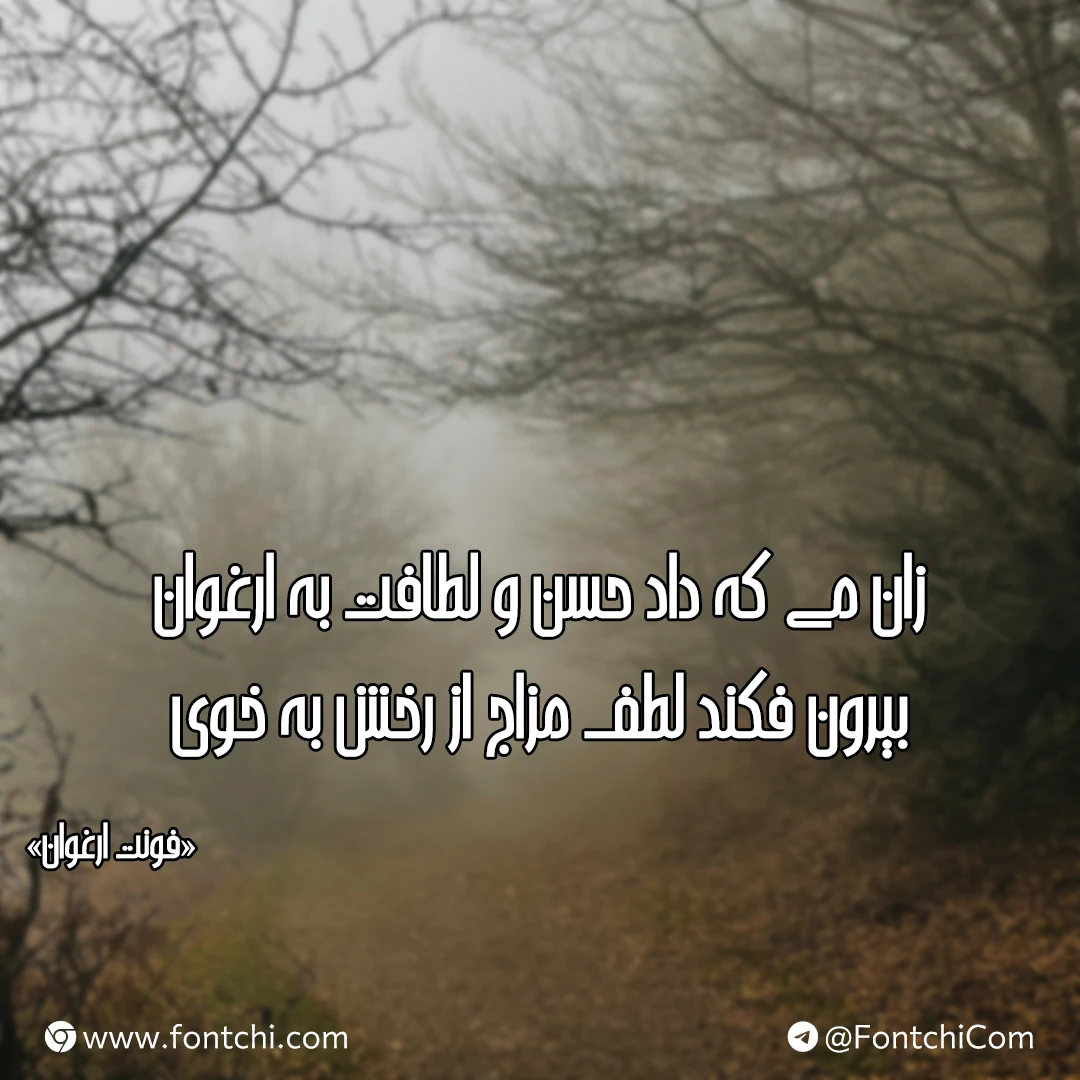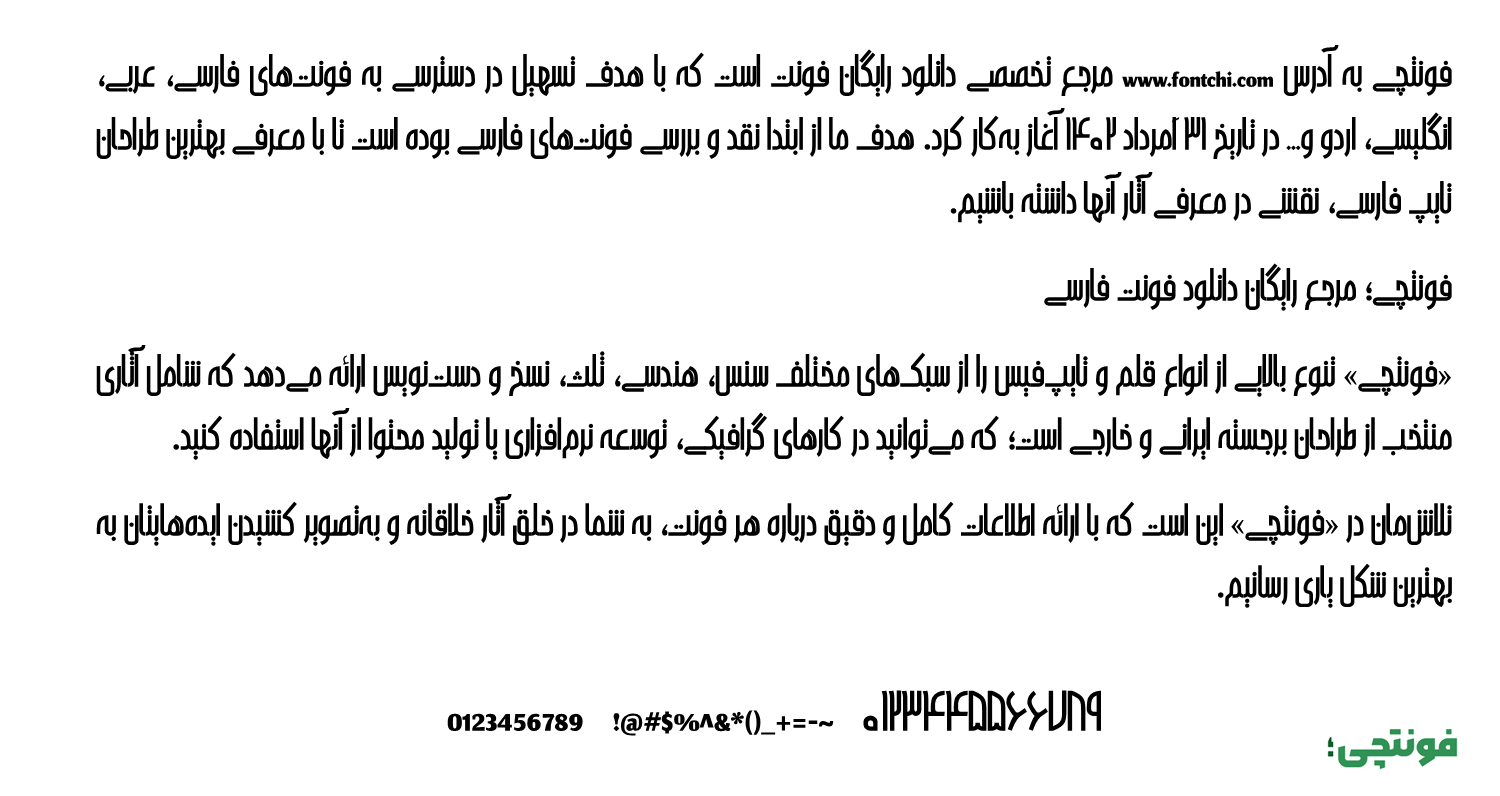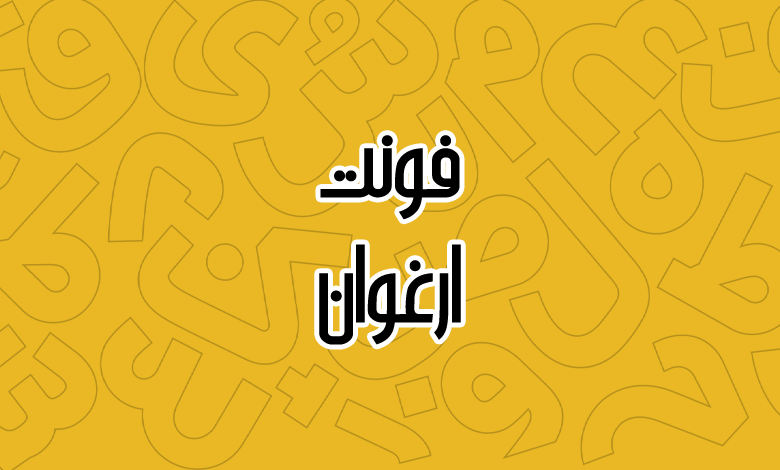
فونت ارغوان (A Arghavan)
فونت ارغوان (به انگلیسی: Arghavan) از سری فونت‌های نمایشی با وزن ضخیم بولد (Bold) است که می‌توانید از آن برای عناوین و متون کوتاه استفاده کنید. فونت فارسی ارغوان دارای ظاهری با ارتفاع بالا و کشیده است که برای جلب توجه در متون تبلیغاتی یا عناوین می‌تواند مورد استفاده قرار گیرد.
طراح این فونت محمو عموئی است که از سبک خاصی برای نقطه‌گذاری این فونت استفاده کرده است. در برخی حروف نقطه‌های دوتایی و سه‌تایی این فونت در کنار یکدیگر و در برخی ترکیبات به منظور نمایشی کردن، به صورت عمود جای گرفته‌اند.
فونت ارغوان از زبان فارسی پشتیبانی کاملی دارد. علاوه بر این از زبان عربی نیز با همین سبک پشتیبانی می‌کند. تنها کاستی برای این زبان، ناهماهنگی اعراب در برخی ترکیبات خاص است. همچنین برای بخش اعداد، به‌جای استفاده از اعداد استاندارد «۰۴۵۶» عربی، از اعداد فارسی «۰۴۵۶» استفاده شده است.
زبان انگلیسی نیز توسط این فونت پشتیبانی می‌شود. اما به دلیل اینکه گلیف اختصاصی خود را نداشته و از قلم دیگری وام گرفته شده است، اندازه حروف کوچکتر از نسخه فارسی بوده و همچنین سبک متفاوت‌تری را دارد. شاید بهتر باشد از فونت مشابه برای زبان انگلیسی استفاده کنید.
هدف از طراحی فونت فارسی ارغوان، نمایشی بوده است. از این فونت می‌توانید برای متون کوتاه چند کلمه‌ای استفاده کنید که جنبه شعار یا جلب توجه داشته باشند. برخی از کاربردهای این قلم عبارتند از:
• استفاده در عناوین کتاب و مجلات
• استفاده بر روی بسته‌بندی محصولات
• استفاده برای تبلیغ محصولات در متن شعارهای برند
• استفاده بر روی تامنیل ویدئوها یا تصاویر پست شبکه‌های اجتماعی
• مناسب در حوزه چاپ و مطبوعات همچون چاپ بنر، بیلبورد و تراکت‌ها
ساختار نمایشی این فونت در عناوین کوتاه، به‌خصوصی وقتی با اندازه بزرگ تایپ شده باشد موجب جلب توجه مخاطبان می‌گردد. فراموش نکنید که از رنگ‌بندی مناسبی نیز استفاده کنید.